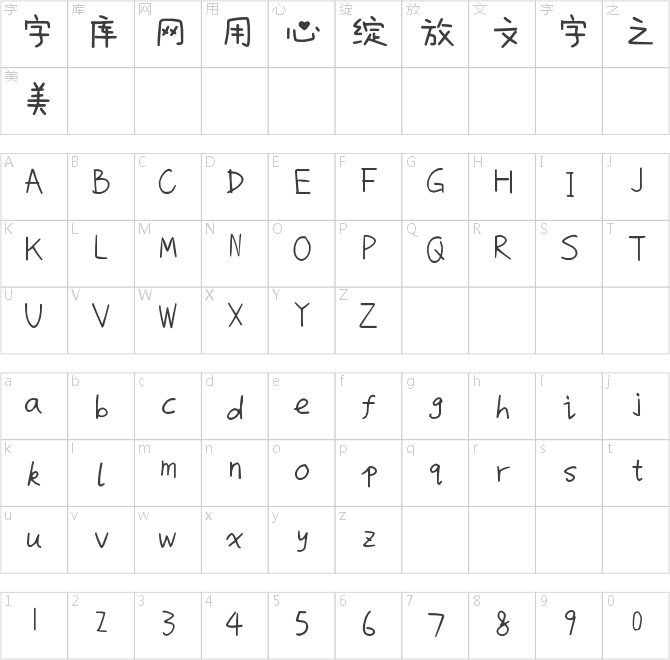
方正手跡-僵尸小可愛(ài) 詳情頁(yè)
方正手跡-僵尸小可愛(ài)字體字庫(kù)是一款讓人賞心悅目、百看不厭的中文字體,適合各類(lèi)廣告和產(chǎn)品包裝設(shè)計(jì)應(yīng)用,字體大小3.26MB,格式為T(mén)TF字體,上傳用戶(hù)是sun *,作者/版權(quán)方為方正手跡